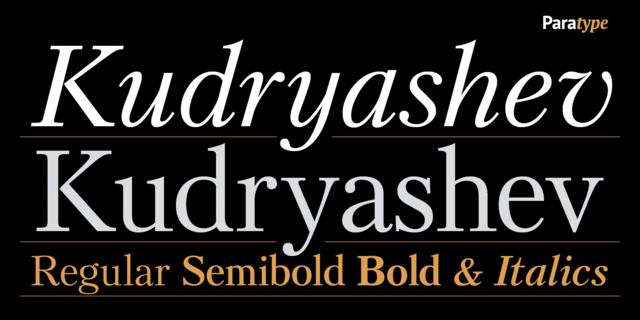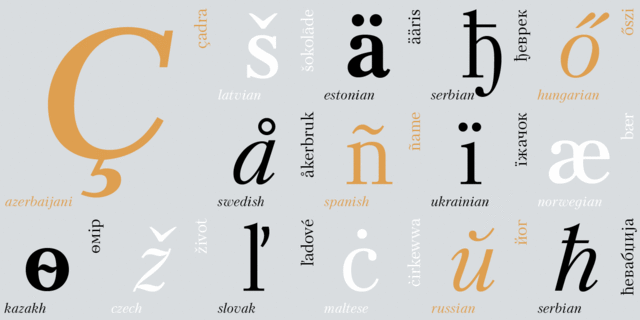
Гарнитура Кудряшевская (ранее известная как Кудряшевская энциклопедическая) была создана с 1960 по 1974 годы Николаем Кудряшевым и Зинаидой Масленниковой в Отделе наборных шрифтов НИИ Полиграфмаш по заказу издательства 'Большая Советская Энциклопедия'. Новая исправленная цифровая версия, расширенная по составу знаков, разработана Натальей Васильевой и выпущена компанией ПараТайп в 2008 году.
благородний, консервативний, традиційний, класичний, оповідний, художній, сріблястий, освічений, гострий, майстерний, точний, аристократичний, елітний, правильний, статичний, комільфо, пафосний, гармонійний, історичний, гуманітарний, срібний, ввічливий, витончений, манірний, красивий, акуратний, поважний, старанний, тактичний, ліричний